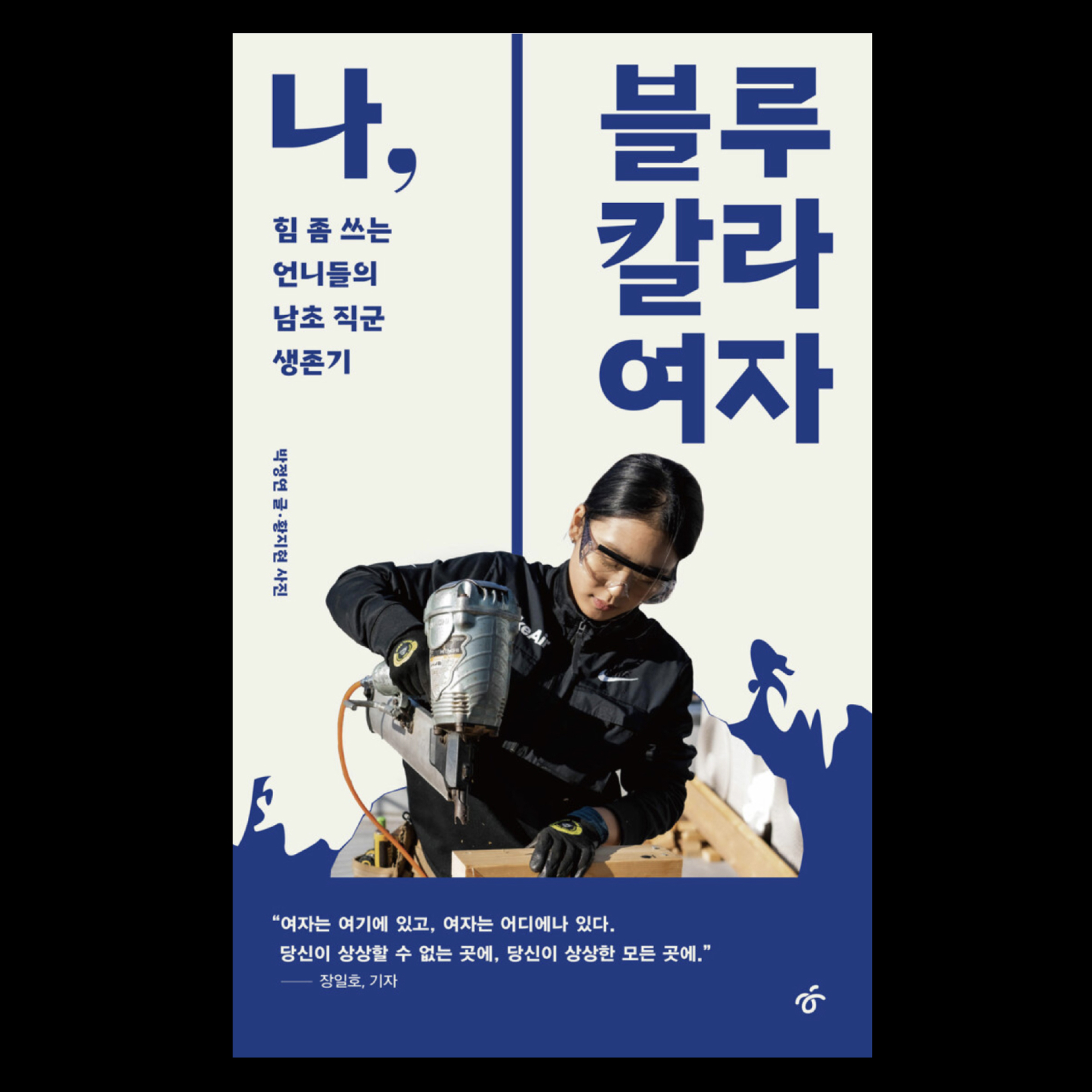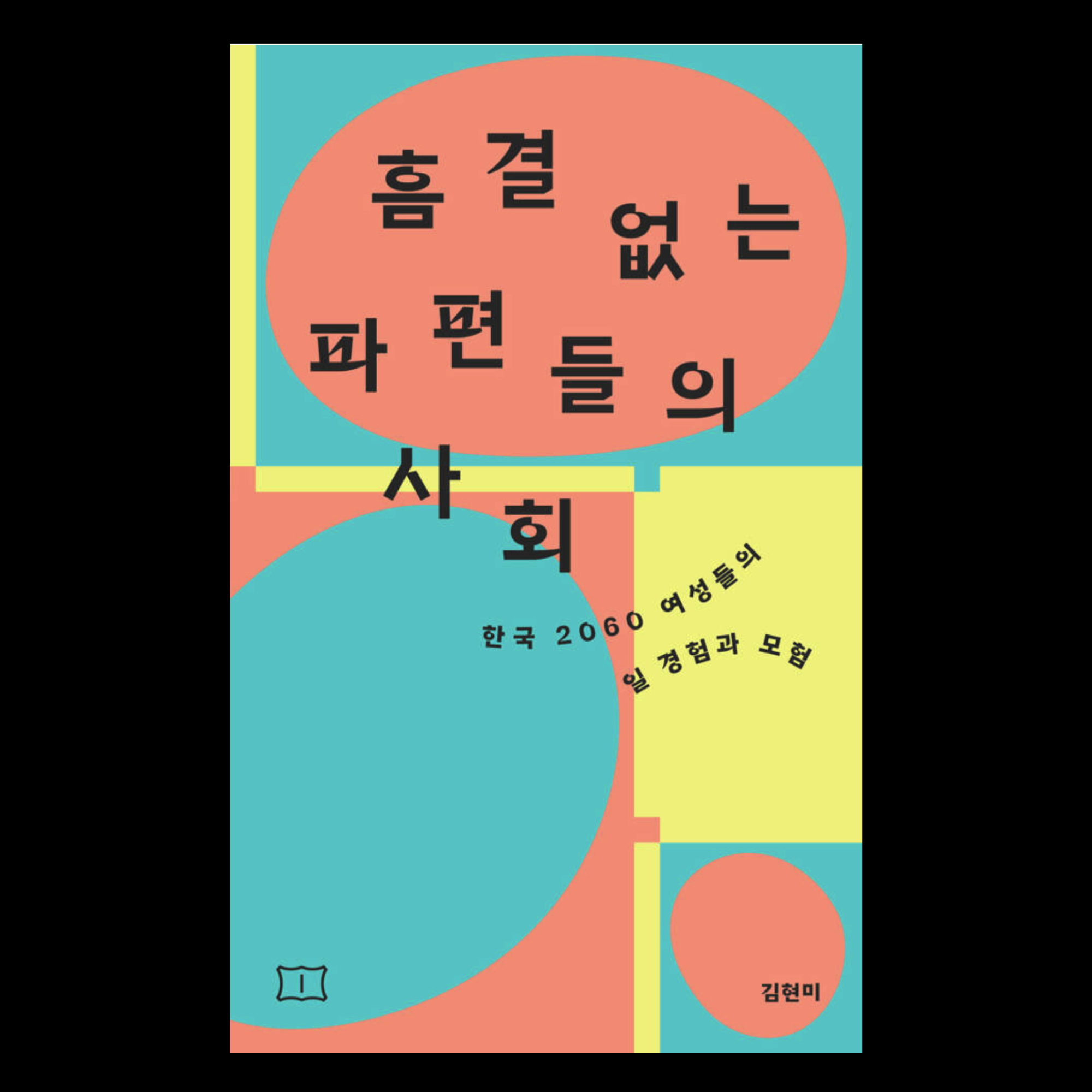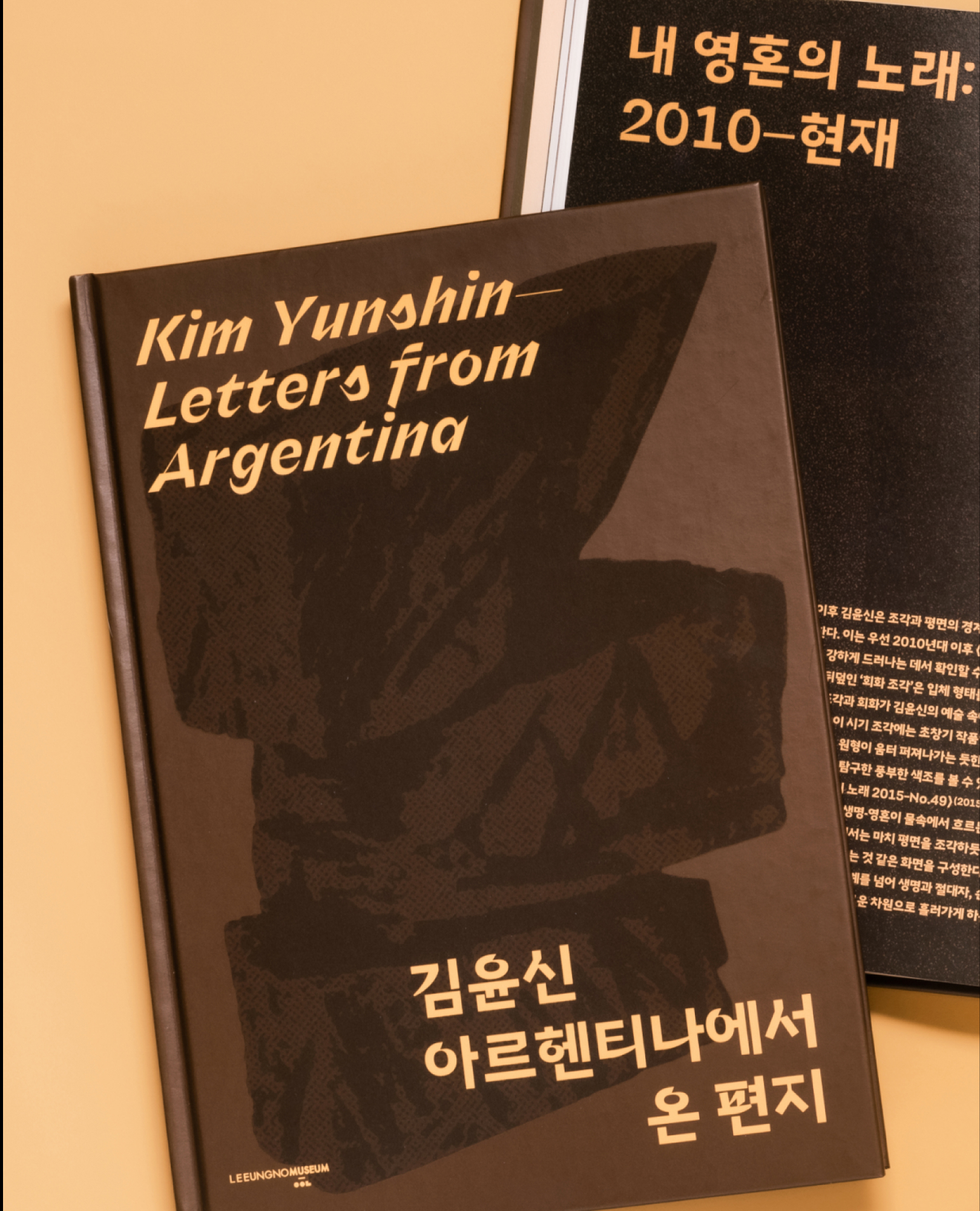
오흐당크 한글 Display 패밀리
Ortank Hangeul Display Family
‘오흐탕크 (Ortank) 한글 텍스트 / 디스플레이’는 지오매트릭 그로테스크 계열의 서체로 기하학적 형태의 한계를 탐구한 결과물인 오흐탕크 텍스트(Ortank Text), 오흐탕크 디스플레이 (Ortank Display)의 한글 버전입니다. 직선형 그로테스크 스타일에서 오는 약간의 고전적인 느낌에 단순함이 결합되었습니다. 서체는 큰 단락 형식뿐만 아니라 작은 텍스트까지 여러 종류의 콘텐츠에서 사용이 가능합니다. 디지털 느낌의 오흐탕크 텍스트는 어느 크기에서든 알맞게 가독성을 최대한 유지합니다. 디지털 느낌의 파격적인 디자인을 지닌 오흐탕크 디스플레이는 굵기가 커질수록 디자인 의도가 더 선명하게 드러납니다. 디스플레이만의 독특한 모양들을 체험해 보실 수 있습니다. 오흐탕크 텍스트 / 디스플레이 글꼴가족은 각각 9종(Thin, ExtraLight, Light, Regular, Medium, SemiBold, Bold, ExtraBold, Black)의 굵기들로 구성되어 있으며 가변 글꼴(축: 굵기, 광학크기)도 별도로 제작해 사용범위를 확장했습니다. 새로운 매력을 지닌 서체, ‘오흐탕크 한글 (텍스트 / 디스플레이)’를 사용해보세요!
‘오흐탕크(Ortank) 한글 텍스트 / 디스플레이’는 지오매트릭 그로테스크 계열의 서체로 기하학적 형태의 한계를 탐구한 결과물인 오흐탕크 텍스트(Ortank Text), 오흐탕크 디스플레이 (Ortank Display)의 한글 버전입니다. 직선형 그로테스크 스타일에서 오는 약간의 고전적인 느낌에 단순함이 결합되었습니다.
서체는 큰 단락 형식뿐만 아니라 작은 텍스트까지 여러 종류의 콘텐츠에서 사용이 가능합니다. 디지털 느낌의 오흐탕크 텍스트는 어느 크기에서든 알맞게 가독성을 최대한 유지합니다. 디지털 느낌의 파격적인 디자인을 지닌 오흐탕크 디스플레이는 굵기가 커질수록 디자인 의도가 더 선명하게 드러납니다. 디스플레이만의 독특한 모양들을 체험해 보실 수 있습니다. 오흐탕크 텍스트 / 디스플레이 글꼴가족은 각각 9종(Thin, ExtraLight, Light, Regular, Medium, SemiBold, Bold, ExtraBold, Black)의 굵기들로 구성되어 있으며 가변 글꼴(축: 굵기, 광학크기)도 별도로 제작해 사용범위를 확장했습니다. 디지털 느낌의 오흐탕크 텍스트는 어느 크기에서든 알맞게 가독성을 최대한 유지합니다. 디지털 느낌의 파격적인 디자인을 지닌 오흐탕크 디스플레이는 굵기가 커질수록 디자인 의도가 더 선명하게 드러납니다. 디스플레이만의 독특한 모양들을 체험해 보실 수 있습니다. 오흐탕크 텍스트 / 디스플레이 글꼴가족은 각각 9종(Thin, ExtraLight, Light, Regular, Medium, SemiBold, Bold, ExtraBold, Black)의 굵기들로 구성되어 있으며 가변 글꼴(축: 굵기, 광학크기)도 별도로 제작해 사용범위를 확장했습니다.